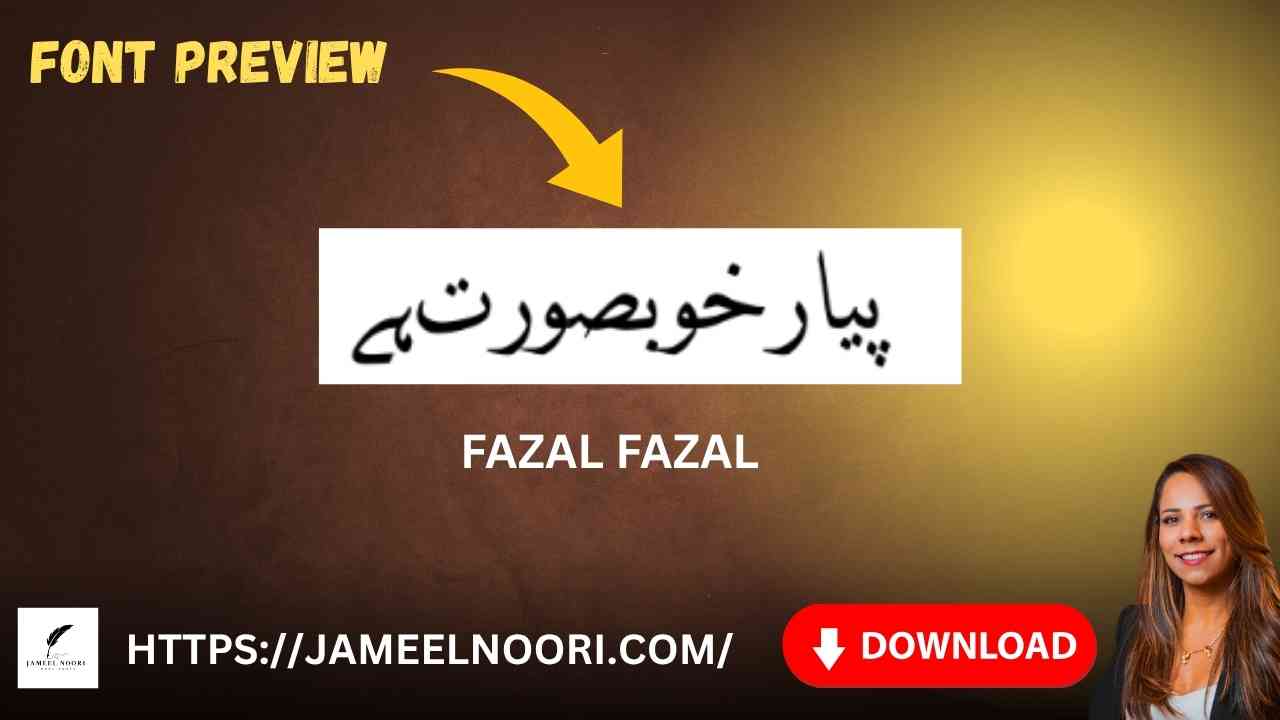
Agar aap Urdu me likhne ke liye aik stylish aur readable font dhoondh rahe hain, to Download Urdu font Fazal Fazal aap ke liye best choice hai. Ye font TrueType format me aata hai jo Windows aur Mac dono par support karta hai. Pakistan me specially designers aur writers is font ko Lahore, Karachi, aur Islamabad jese cities me extensive use karte hain.
Fazal Fazal font ki kuch zabardast features ye hain jo ise best Urdu font banati hain:
Download Urdu font Fazal Fazal kahan use hota hai?
Ye font aksar Urdu novels, social media graphics, Islamic calligraphy aur PDF books me use hota hai. Kuch popular usage areas:
- Blog aur article writing
- Wedding cards aur invitation templates
- YouTube Urdu thumbnails
- Islamic quote design
Download Urdu font Fazal Fazal – Why It’s an Expert Choice in Pakistan
Yeh font itna popular is liye hai kyun ke:
- Simple aur elegant design har reader ko pasand aata hai
- Lightweight hone ki wajah se system par burden nahi daalta
- Professional look deta hai jese Jameel Noori Nastaleeq
- Graphic designers aur bloggers isay daily projects me use karte hain
- Stylish aur readable Urdu text
- Best for bloggers, designers, and publishers
Akhir mein, Download Urdu Font Fazal Fazal ek behtareen choice hai un logon ke liye jo Urdu typing ko stylish aur professional touch dena chahte hain. Iska clean aur readable design har tarah ke projects — chahe wo books, graphic designing, ya social media posts hon — mein behtareen kaam karta hai. 2025 ke is updated guide mein aapne is font ki features, installation process aur usage ke bare mein detail se jana. Ab aap asani se is font ko download karke apne creative projects ko ek naya look de sakte hain.
Is Fazal Fazal better than Jameel Noori?
Both are good; Fazal Fazal is simpler and cleaner, while Jameel Noori is more calligraphic.